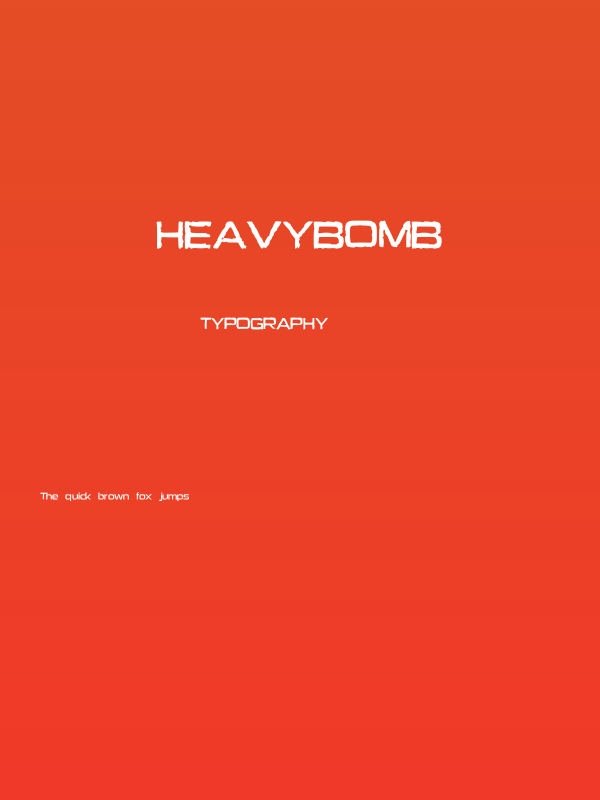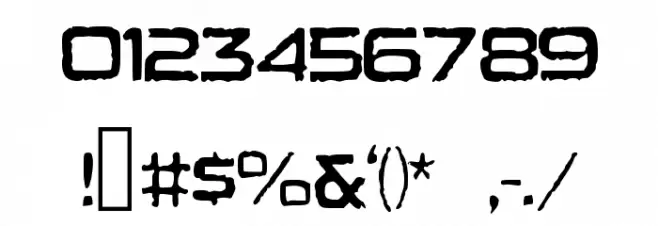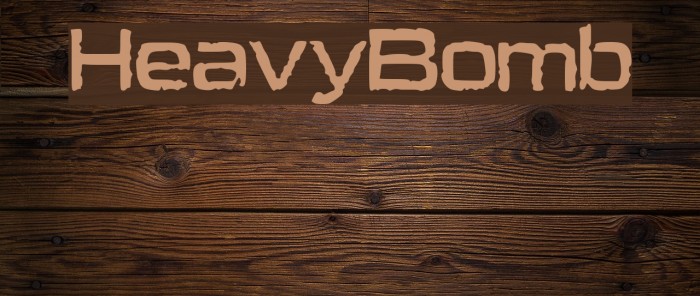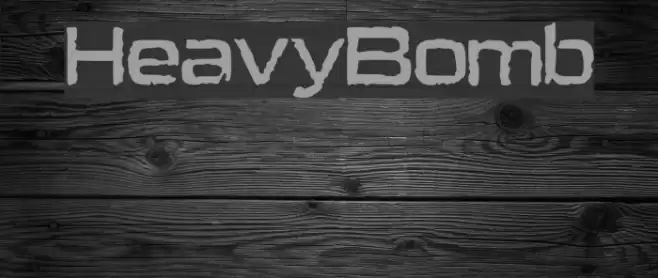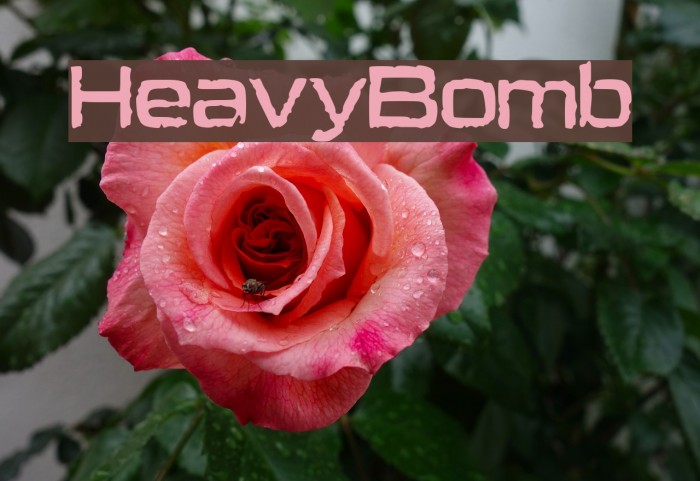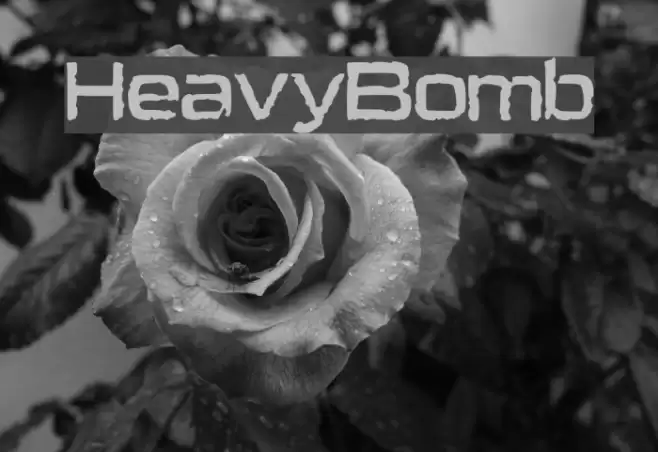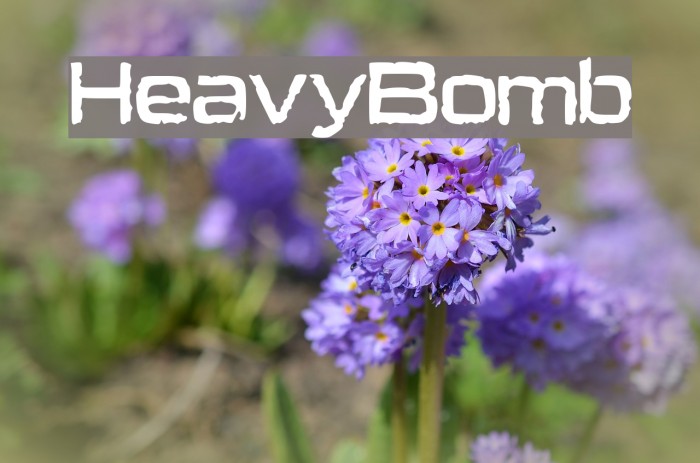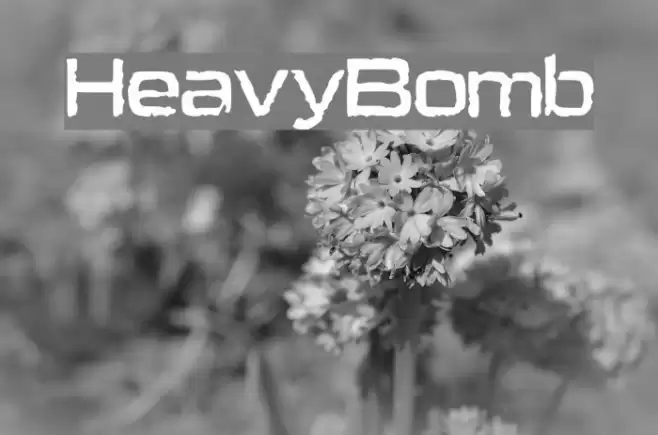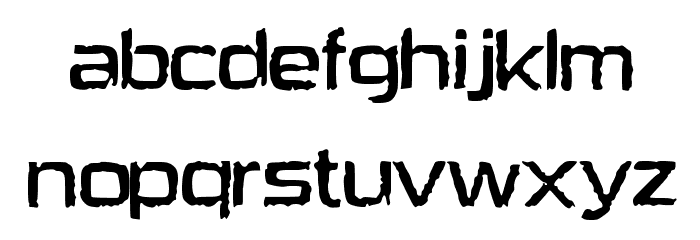
HeavyBomb Font
✎ Distorted Eroded
| Progetti proposti | Ideal for posters, album covers, video game graphics, and branding that requires a bold, edgy look. |